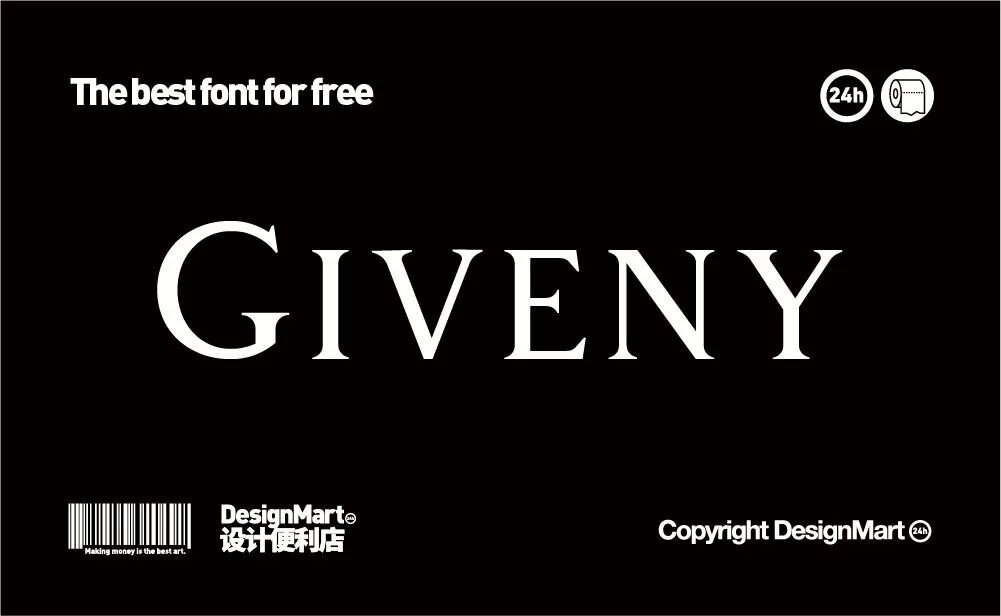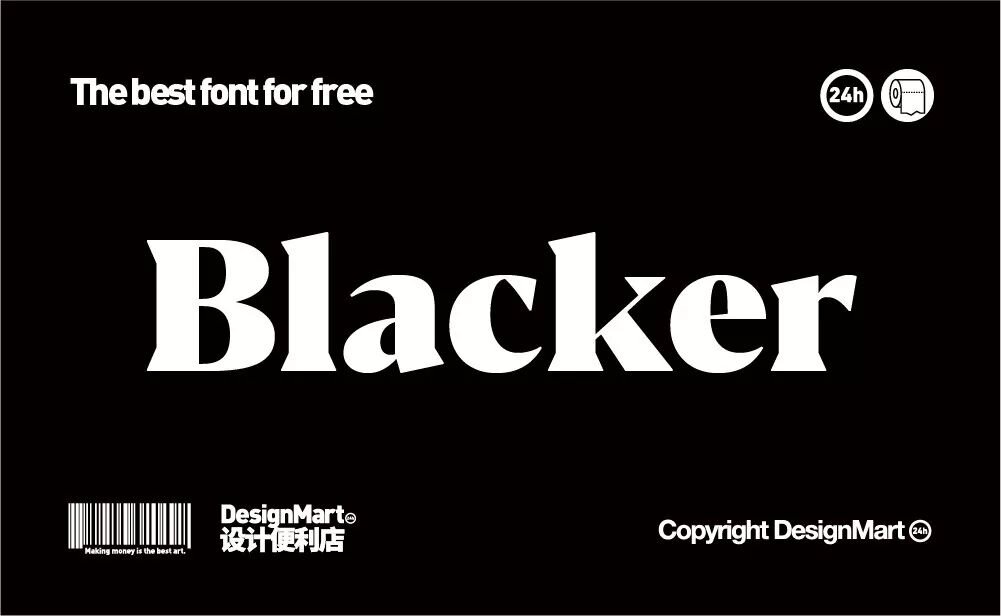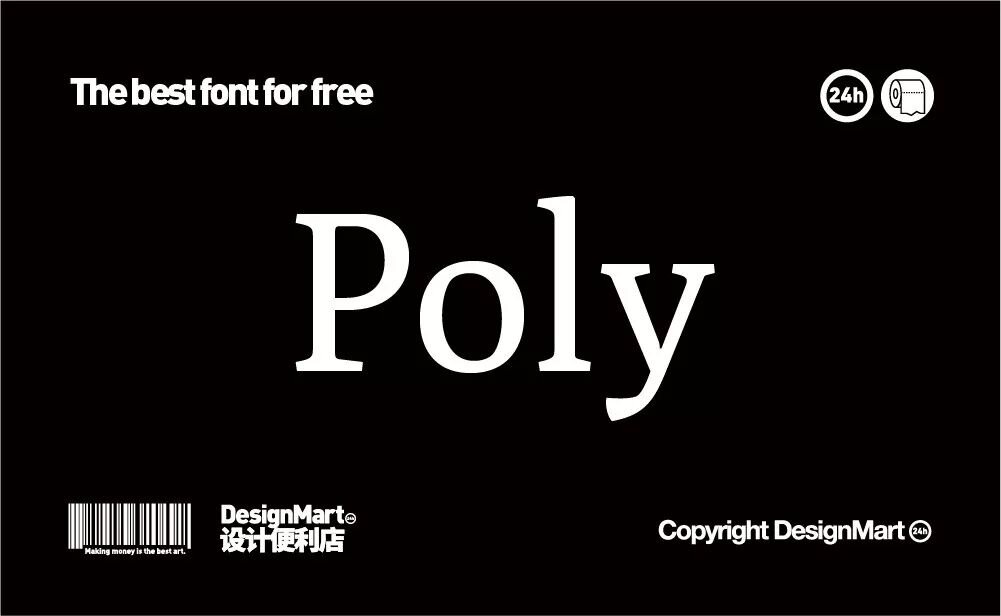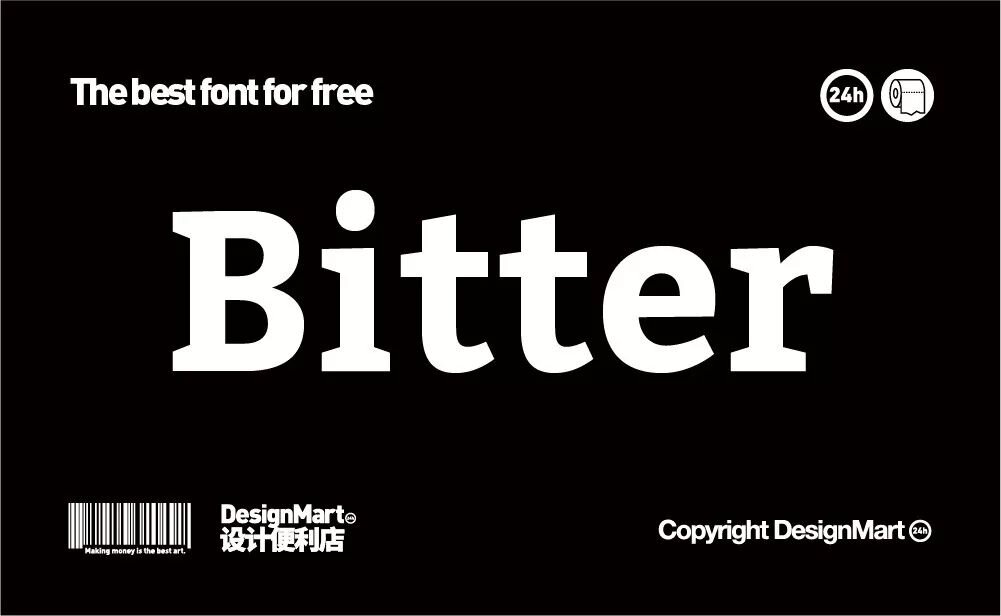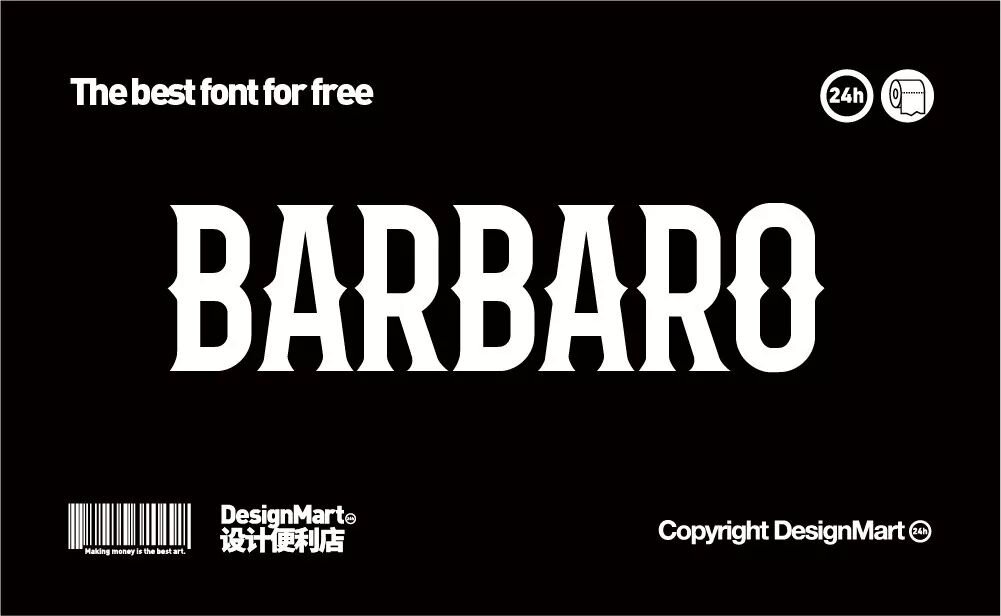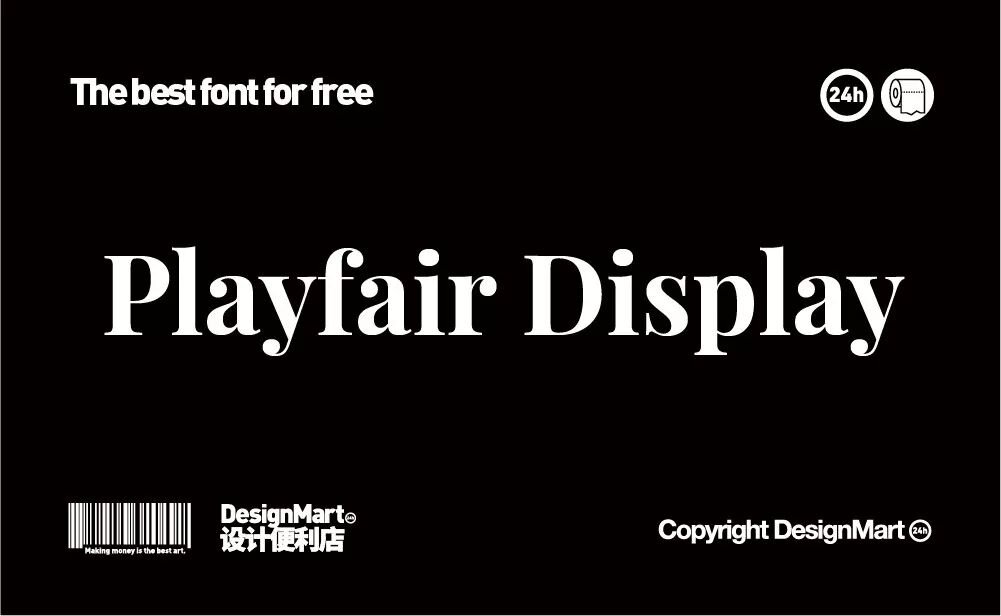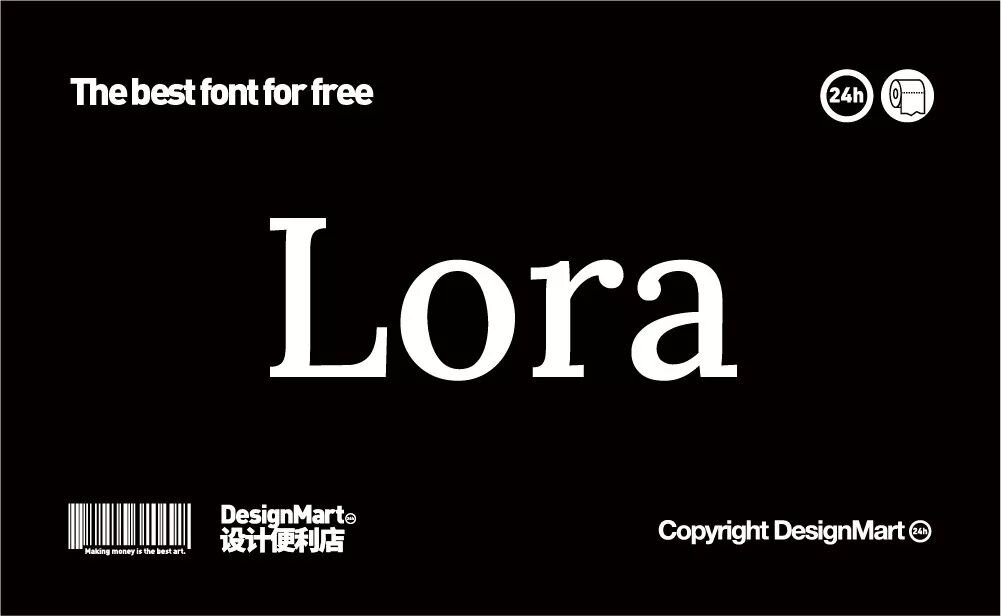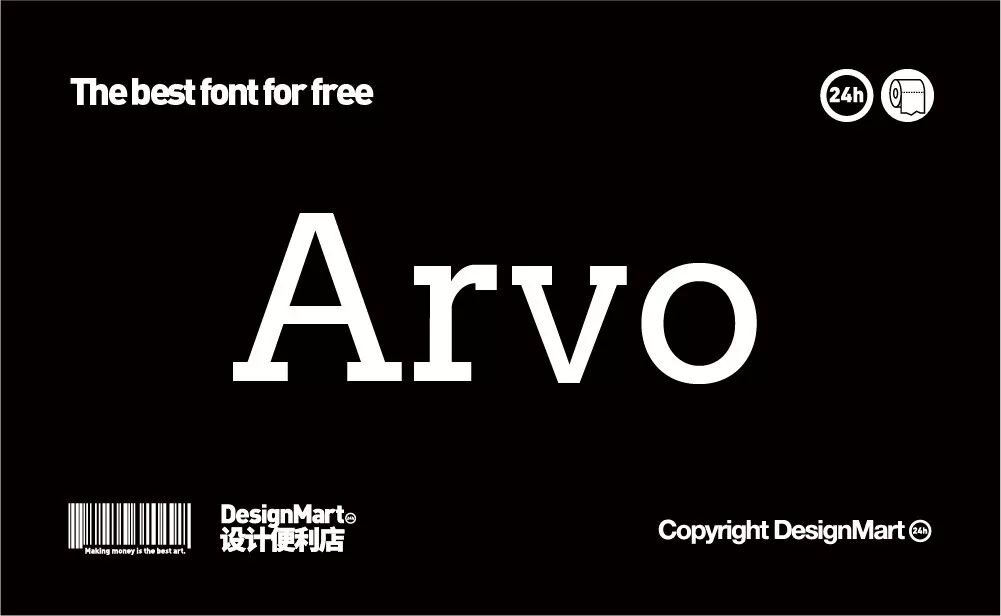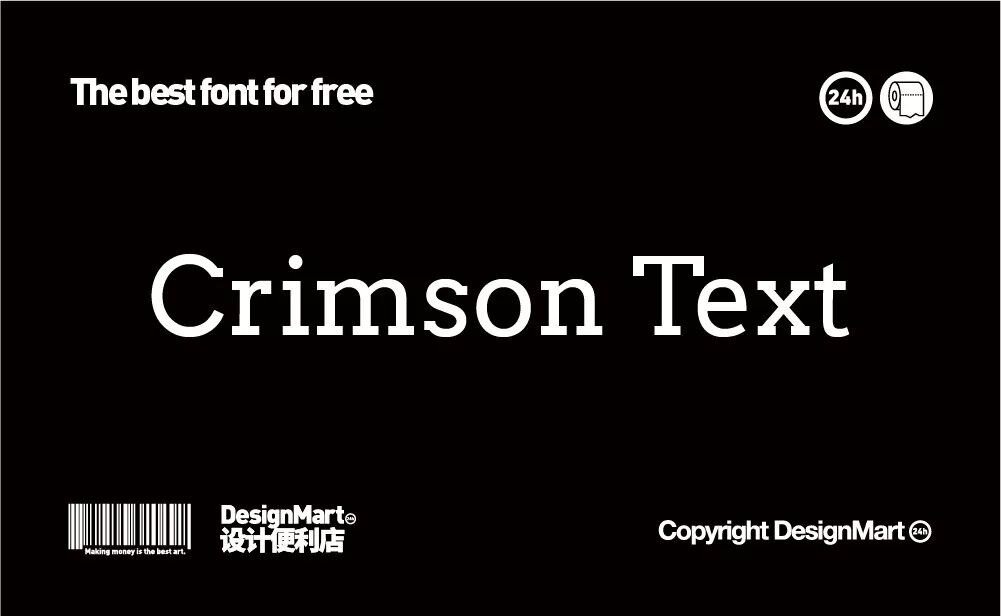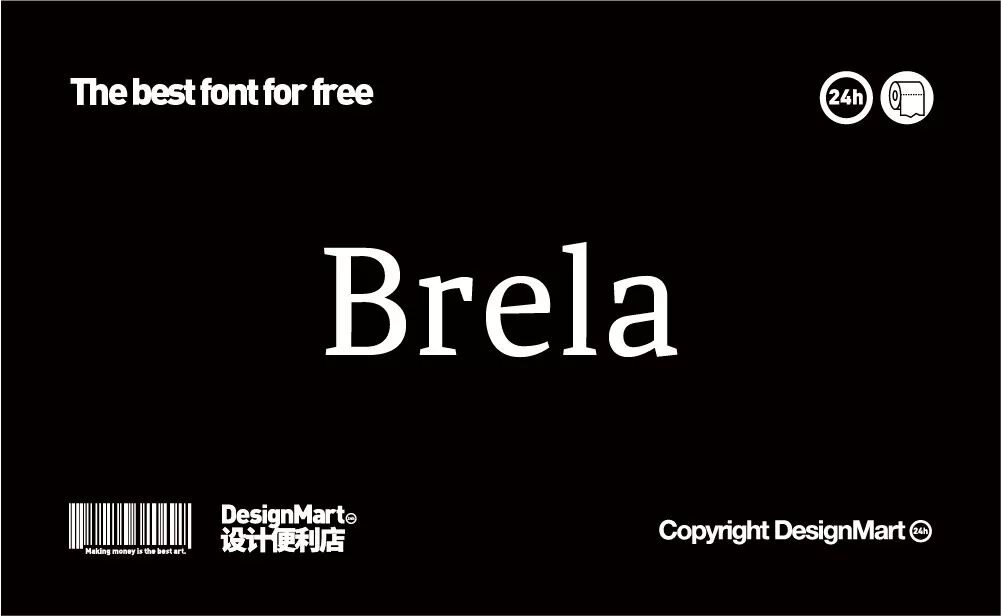
Giveny
這款優雅的免費字體可以給設計帶來極強的精緻感。並且適用範圍相當廣泛,由Craft Supply Co.設計完成。提供多種語言字符,以及一系列標點符號。
Blacker
Blacker並不是一款傳統的襯線字體,從經典設計中汲取靈感調整而來,設計師認為它是一種當代邪惡襯線體,具有高度的識別度、年代感的比例和尖銳的楔形襯線,字重非常全面,不過只有其中兩款是完全免費。
字重:Light、Medium Italic
Poly
Poly是一款適用於Web中的襯線字體,即使在較小分辨率下也有非常優秀的易讀性,它利用短的升部和非常高的X基線高度來確保字體識別的清晰度。
Bitter
同樣是一款能夠在屏幕中表現優秀的襯線字體,它結合了常規的X基線高度且在粗細結構對比中使用了最小的變化。
Barbaro
BarBaro包含了兩個不同的字體風格,看起來哥特的風格讓它能很好的運用在復古風格強烈的海報或是品牌設計中。
Playfair Display
這是一款完全免費的開源字體,包含眾多字重和格式,可以完美兼容不同操作系統,Playfair的靈感來自於18世紀晚期的歐洲藝術啓蒙運動。
Lora
Lora是一款源於書法體的免費字體,最初由Cyreal設計,曲線部分和襯線部分的鮮明對比,賦予了這款字體均衡的現代感,儘管Lora在技術上已經經過優化,可用於網路呈現,但是它依然更是用於印刷項目。
Butler
這款字體受到Dala Floda和BodoniPoly的影響,在經典的襯線體基礎上,帶來了一些現代主義,這款字體字重非常全面,且支持多種語言,標點符號和額外字型。
Arvo
Arvo是一種幾何平板襯線字體,適用於屏幕和打印用途,它專門為易讀性而設計,作為免費開源字體在Google Font上發佈,與Google中許多平板襯線不同,Arvo包含更多字重。
Crimson Text
這是一款專門為圖書製作而設計的免費字體系列,靈感來自於古老的Garamond式書籍字體,它具有非常富有表現力的斜體,與Futura或Avenir搭配都非常好用。
Aleo
Aleo具有半圓形細節和光滑的結構,給人一種個性感,同時保持良好的易讀性。這個免費的字體系列包括六種風格:三種重量(淺色,常規和粗體),以及相應斜體。
Brela
Brela是一款非常人性化的襯線字體。它具有寬大的x高度,即使在很小的尺寸下也非常清晰,但它同樣也適用於誇張的大標題,這個免費的字體是由西班牙創意機構馬卡爾斯卡工作室設計。
Libre Baskerville
這是一款針對正文文字(通常為16px)優化的Web字體,他通過更高的X高度和更低的對比度,使其能夠很好的在屏幕上閱讀,這個字體還有一個姐妹字體Libre Franklin,也是免費字體哦。
Slabo
Slabo是一系列不斷增長的特定尺寸的網絡字體, 到目前為止,Slabo 27px和Slabo 13px已經完成,可以精確調整以適應特定像素尺寸。其結構的塊狀感賦予襯線字體的現代感,非常適合在線設計。
Bree Serif
由獨立字體設計廠牌TypeTogether創建,Bree Serif是付費字體系列Bree的免費襯線表兄弟。Bree Serif被描述為「友好的直立斜體」,十分現代化,在較大的尺寸使用時具有相當優秀的易讀性。
Merriweather
Merriweather是一款真正開源的免費襯線字體,在GitHub上有自己的項目。它由Sorkin Type設計,十分易於在屏幕上閱讀,並且在在Google Fonts中有非常高的人氣!
Manrope
又是一個開源字體系列,專為多種現代用途而設計,適用於標題,段落,印刷品和網絡。這是該字體的第二個版本,有七種樣式。沒有斜體(創作者認為在現代不需要斜體),字體涵蓋了大多數拉丁語和西里爾語。
Kano
Kano是一種幾何字體,看起來像大寫字母,但也適用於正文。
Alcubierre
Kano是一種幾何字體,看起來像大寫字母,但也適用於正文。
Moon
Moon是一種圓形的無襯線字體,有三種重量,最近更新為包含小寫字母。Moon對於個人項目是免費的,但如果你想在商業上使用它,你需要支付許可費。